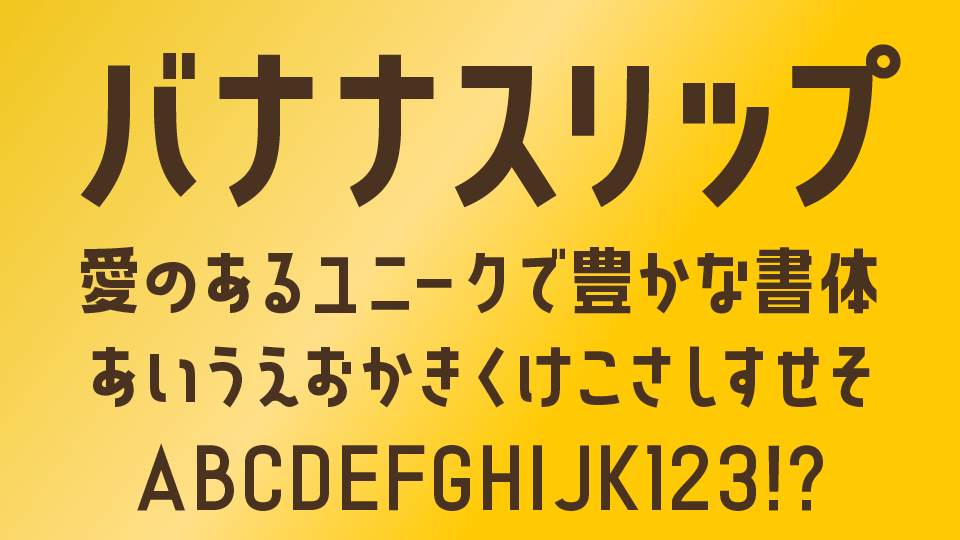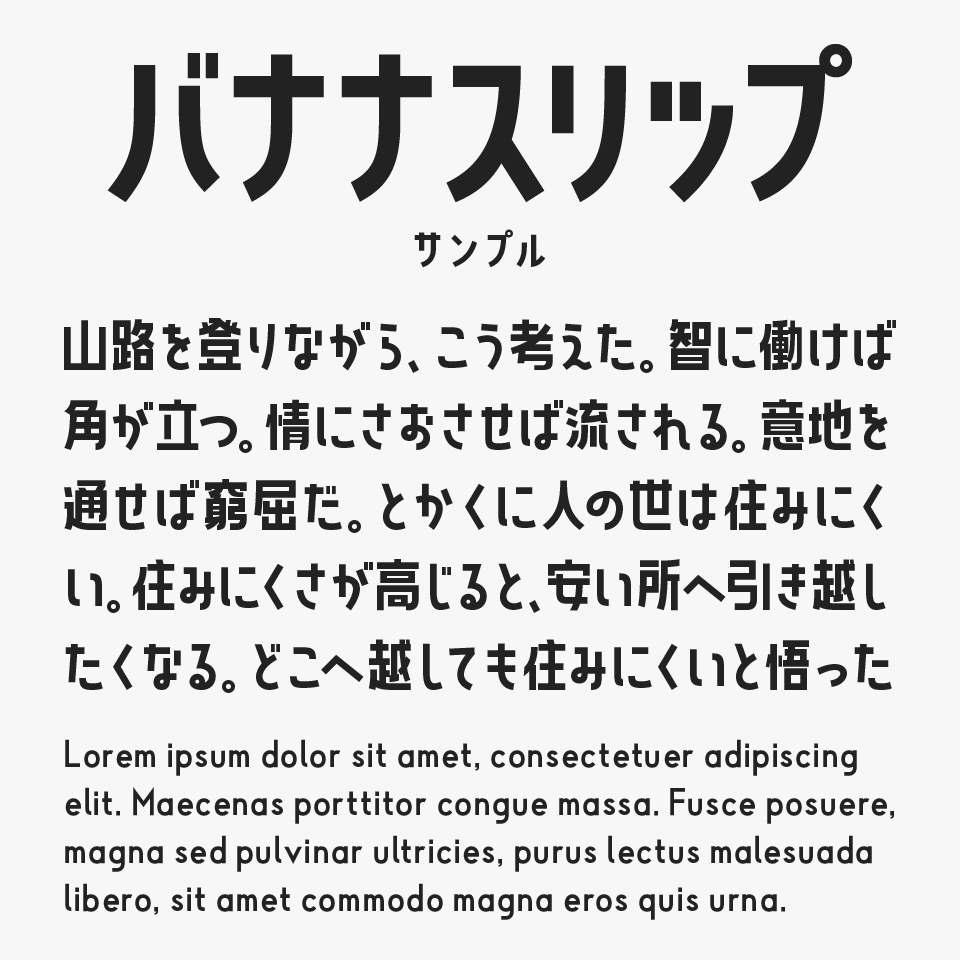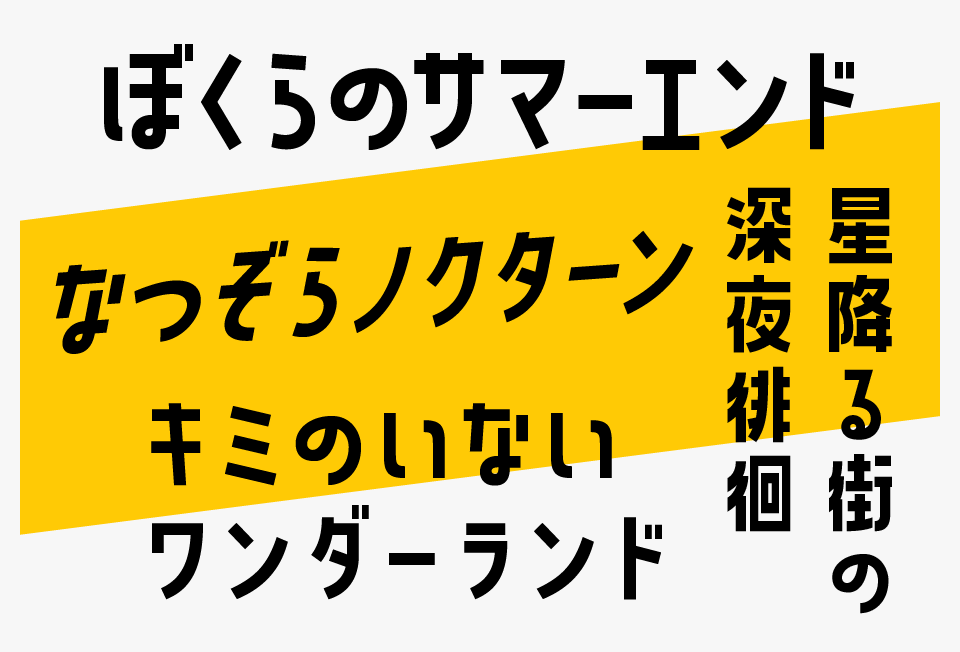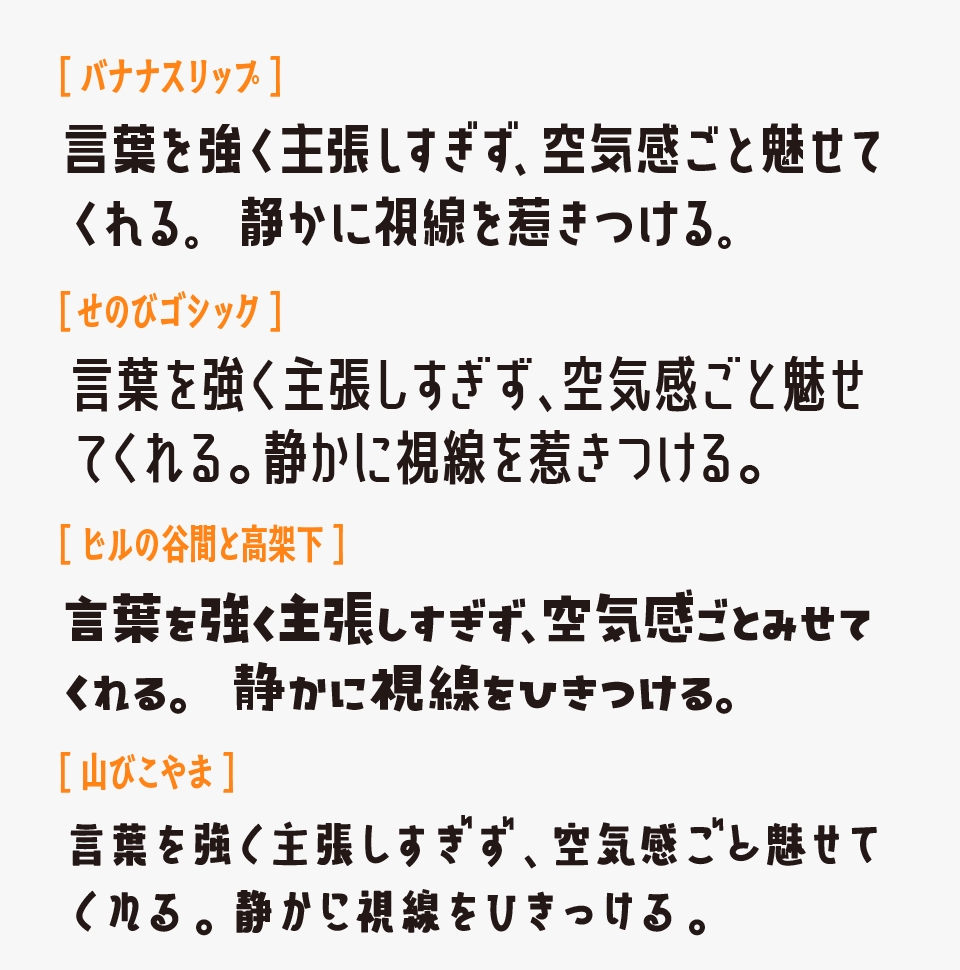
バナナスリップ
バナナスリップフォントは、太くしっかりとした骨格を持ちながらも、ほんのり可愛らしさが感じられる絶妙なバランスのデザインフォントです。
「堅苦しくしたくないけれど、可愛すぎる雰囲気にもしたくない」そんな場面にぴったりで、ポップさとスタイリッシュさをちょうどよくバランスのフォントです。
直線的な線で構成されているため、全体にはスッキリとした印象がありますが、文字のリズム感やシルエットによって、どこか親しみやすい空気感を感じます。
特に、漢字に対してかな文字が少し小ぶりに設計されていることで、文字組みに独特なまとまりが生まれており、縦長のフォルムとあわせて、軽快で洗練された雰囲気を楽しめるフォントとなっています。
存在感のある太さを持ちながらも、どこか軽やかで親しみやすい空気感があるため、ポップ系からモダン系まで幅広いデザインに取り入れやすいところも魅力です。
デザイナー人気も高く、バナーやYouTubeサムネイル、SNSビジュアルなどで見かける機会も多く、“今っぽいデザイン感”を演出しやすいフォントとなっています。同人誌のタイトルロゴなどにもぴったりです。
バナナスリップのように、長体スタイルの中に可愛らしさが表現されているフォントと比較してみると、バナナスリップは、特に“親しみやすさ”と“かっちり感”のバランスが絶妙のフォントです。
比較フォントは「せのびゴシック」「ビルの谷間と高架下」「山びこやま」を使用していますが、どのフォントもとても可愛らしさがあるので、あわせてチェックしてみてください。